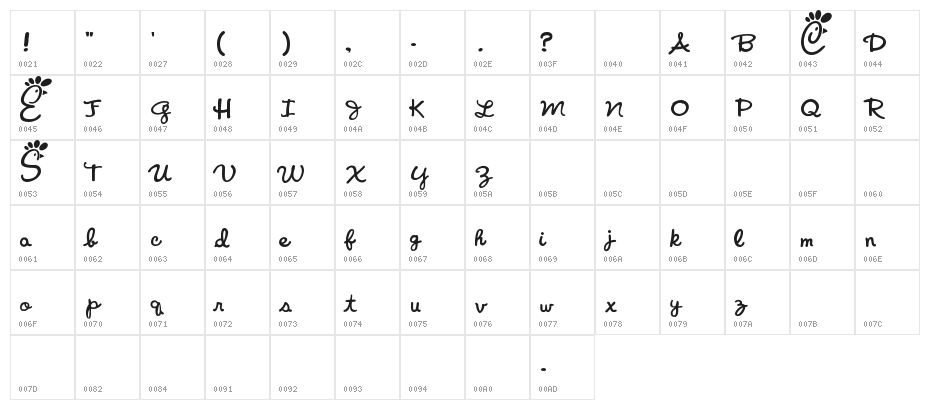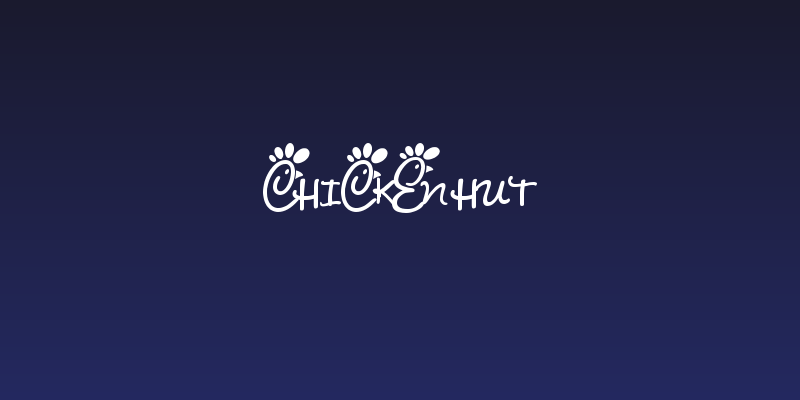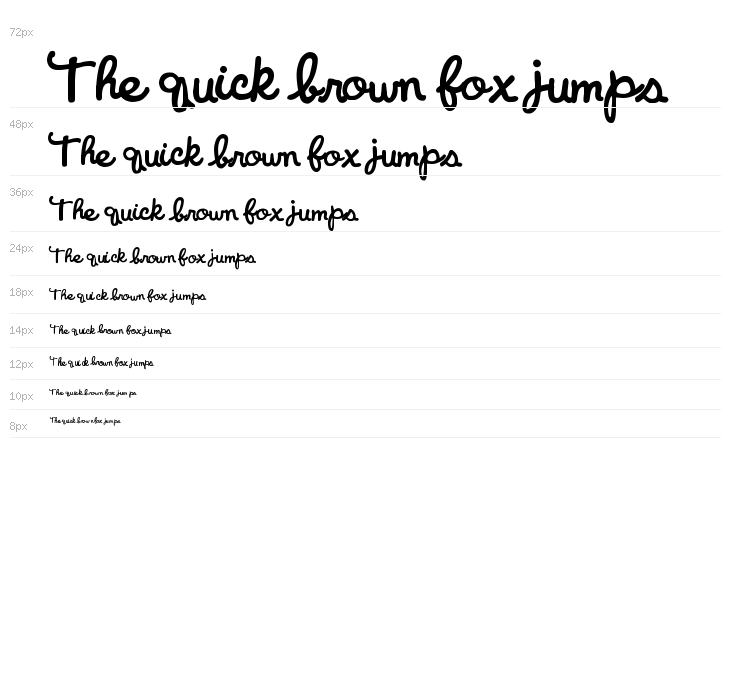
Chicken Hut Font
| Stile generale | Playful, Whimsical |
| Caso d'uso | Logos, Invitations, Branding |
| Progetti proposti | Ideal for children's books, pet-related branding, playful invitations, and casual greeting cards. |